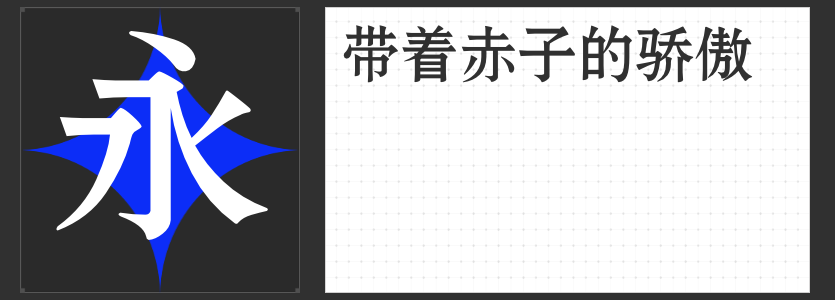
印刷设计中的气质之选:四款匠心字库字体推荐
在印刷设计中,字体不仅是信息的载体,更是视觉美学的核心。一款合适的字体能瞬间提升设计质感,传递品牌调性。今天为大家精选四款兼具艺术性与实用性的字库字体,它们以独特的风格与严谨的工艺,成为高端印刷场景的“点睛之笔”。
一、 励字宋黑简
励字宋黑简以黑体为骨架,融入宋体的典雅气质,打造出横竖分明、结构严谨的视觉效果。其横轻竖重的笔画设计,既保留了黑体的现代感,又赋予文字书卷气息,字形端正大方而不失灵动。无论是书籍正文排版、企业年报,还是文化类海报,这款字体都能以清晰易读性与典雅气质,传递专业与信赖感,尤其适合需要兼顾传统与现代的设计场景。
二、 励字美黑简
励字美黑简巧妙融合黑体与宋体的优势,在保持字形匀称清秀的同时,强化了笔画的力度与节奏感。其视觉效果端庄正气,既不过于锋利,也不显柔弱,恰到好处地平衡了力量感与亲和力。在品牌手册、产品包装、高端杂志等印刷品中,这款字体能以简洁有力的形态,强化品牌的专业形象,同时赋予设计以人文温度。
三、 励字舒体简繁
励字舒体简繁突破传统字体框架,以“师古而不泥古”的理念,将楷、行、隶、草、篆的笔意融为一体,形成飘洒圆秀、沉雄峭拔的独特风格。其字形如行云流水,既有书法的洒脱韵律,又不失印刷字体的规整性。在艺术画册、文化展览海报、高端品牌视觉中,这款字体能以强烈的艺术张力,传递文化底蕴与创新精神,成为设计中的视觉焦点。
四、 励字粗圆简繁
励字粗圆简繁以方正饱满的结构与柔和的笔画,打造出温暖而稳重的视觉体验。其字面较大,笔画粗壮却不显笨拙,反而透露出一种亲切感与包容性。在儿童读物、食品包装、生活类杂志等设计中,这款字体能以柔和的形态拉近与读者的距离,同时以端正大方的气质提升整体设计的品质感。
这四款字体以多元风格满足不同印刷设计需求。它们不仅是工具,更是设计师表达创意的“语言”。无论是追求专业严谨,还是渴望艺术突破,这些字体都能为你的作品注入独特气质,让印刷设计更具生命力。